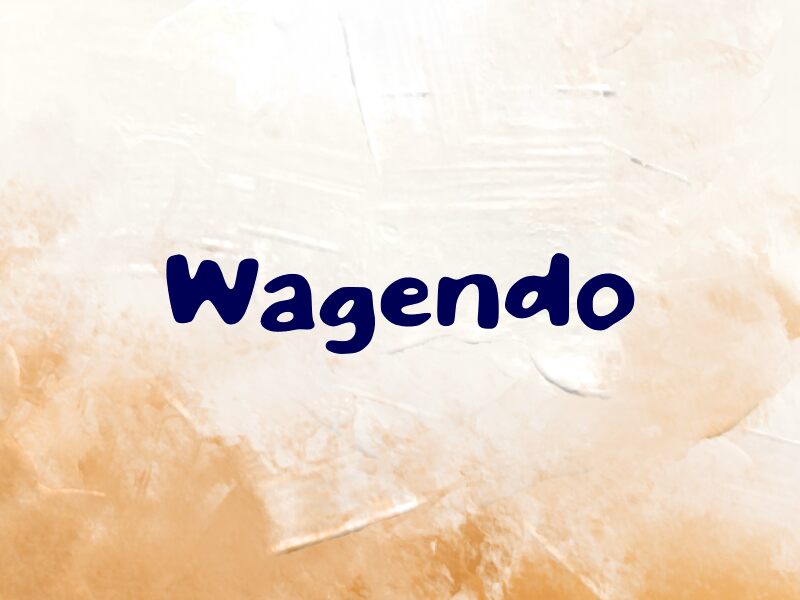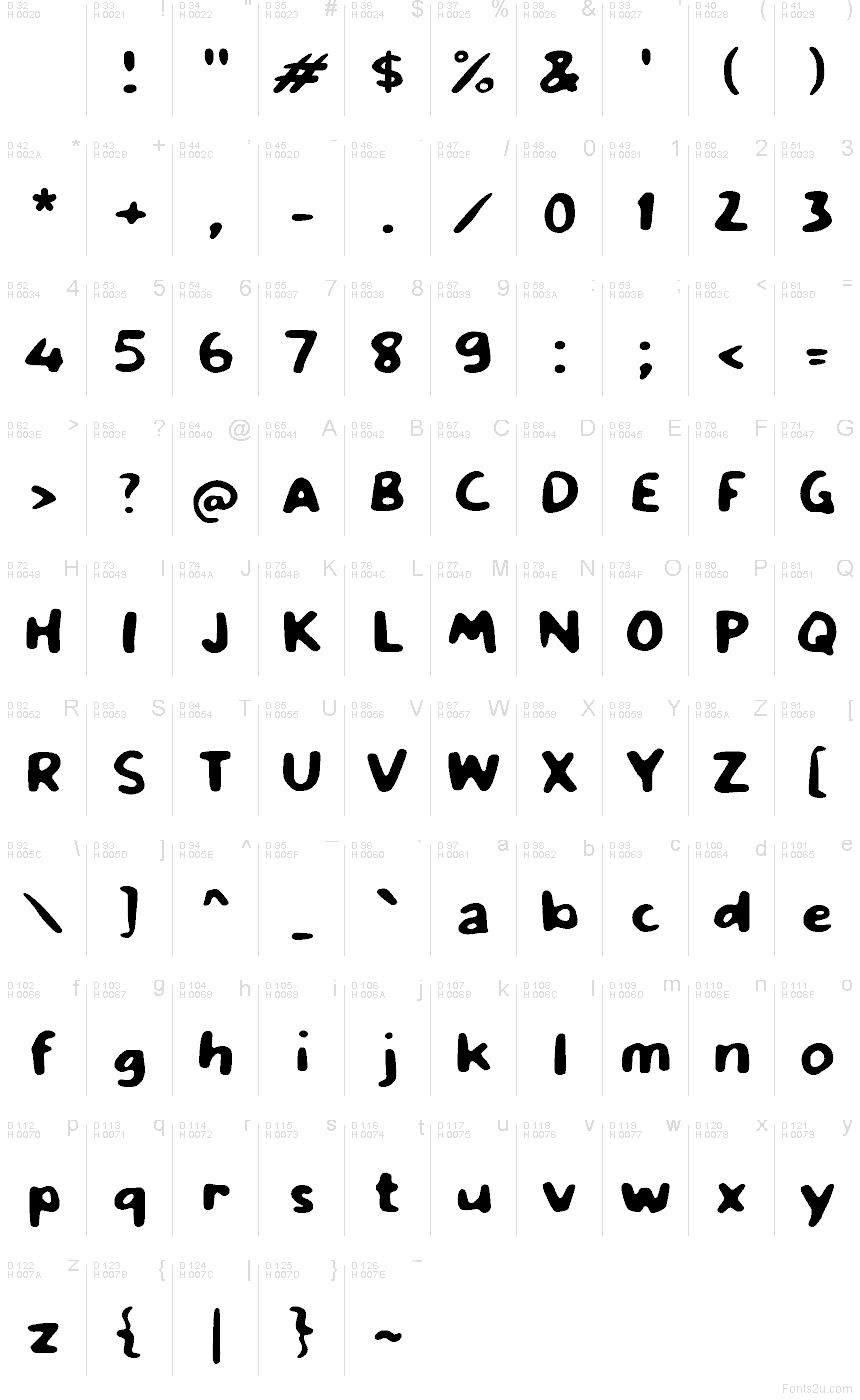
Wagendo, créée par Wep, est une police d'affichage gratuite de type « comic » avec un aspect doux et dessiné à la main. Les caractères sont épais et conviviaux, dotés de bords arrondis, de courbes irrégulières et d'un rythme décontracté qui rappelle davantage une signalétique gribouillée qu'une typographie lisse.
Elle s'intègre parfaitement aux couvertures de livres pour enfants, aux emballages ludiques, aux menus de café, aux designs d'autocollants et aux publications sur les réseaux sociaux, où cette police gratuite apporte une voix chaleureuse et informelle. Grâce à ses formes légèrement tremblantes et globalement arrondies, elle fonctionne aussi très bien pour des cartons de titre ou de courts titres qui se veulent humains et accessibles.
Wagendo
Présentation et spécimen de la police Wagendo
Table des caractères de la police Wagendo
Table des caractères de Wagendo : Latin de base, page 1
Glyphes de la police Wagendo — Latin de base, page 1